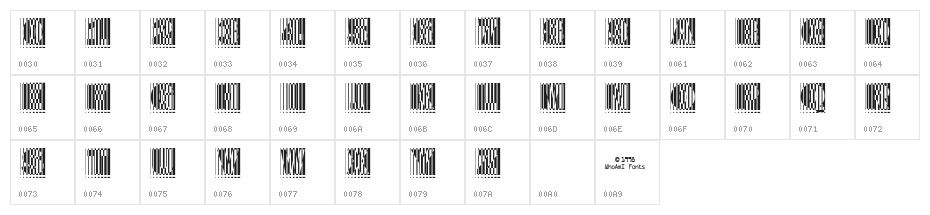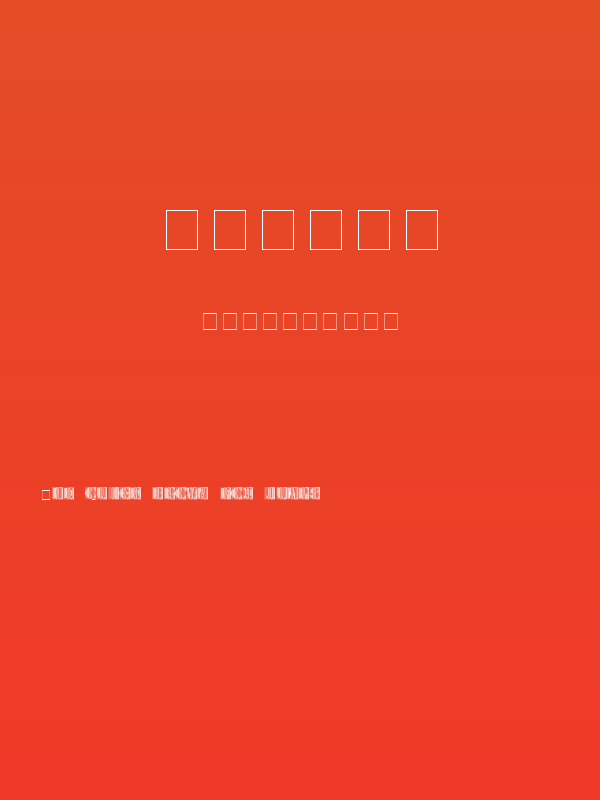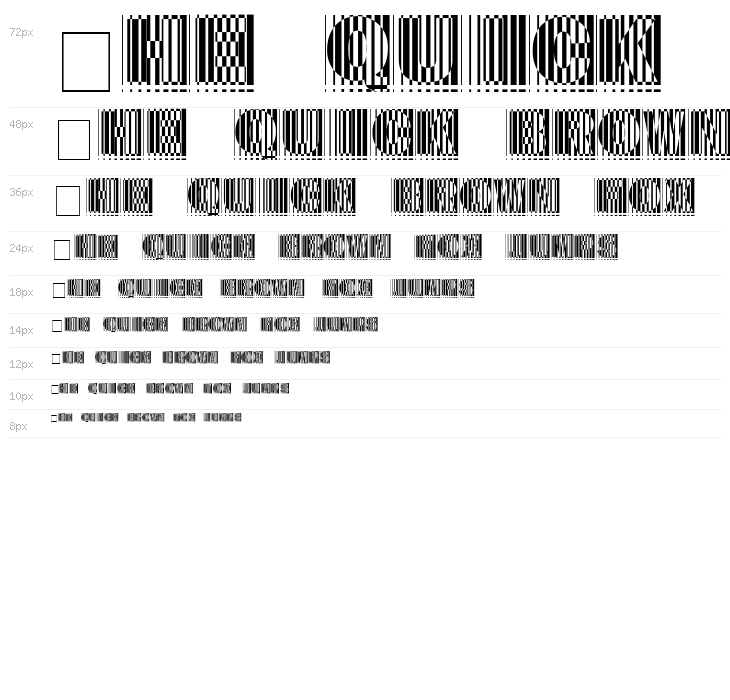
Arrgh! Font
| Gesamtstil | Modern, Industrial |
| Anwendungsfall | Logos, Posters, Thematic Designs |
| Vorgeschlagene Projekte | Ideal for futuristic designs, tech-themed posters, or branding that requires a modern and industrial look. |